AWE2026展会现场
3月12日至15日,2026年中国家电及消费电子博览会(AWE2026)在上海举行。本届展会以“AI科技 慧享未来”为主题,吸引超过1200家国内外企业参展。在这场科技盛宴中,方正字库携“智能家居,字享未来”主题亮相新国际博览中心展区(展位号:W5-5A37),展示为家电行业提供的字体解决方案。
AWE2026展会现场方正字库展位
在人工智能技术深度渗透的当下,方正字库也在尽全力助力企业尽快实现产品、生态智能化。
赋能行业基础:以标准字体服务产业共性需求
在本次展会上,方正字库重点呈现了其在家电标识管理领域的深度参与。根据《能源效率标识管理办法》,标识的样式和规格有着严格规定。作为标识信息中的官方字体,方正字库的多款字体被广泛应用于家电能效标识,确保信息传达的规范、清晰与统一。
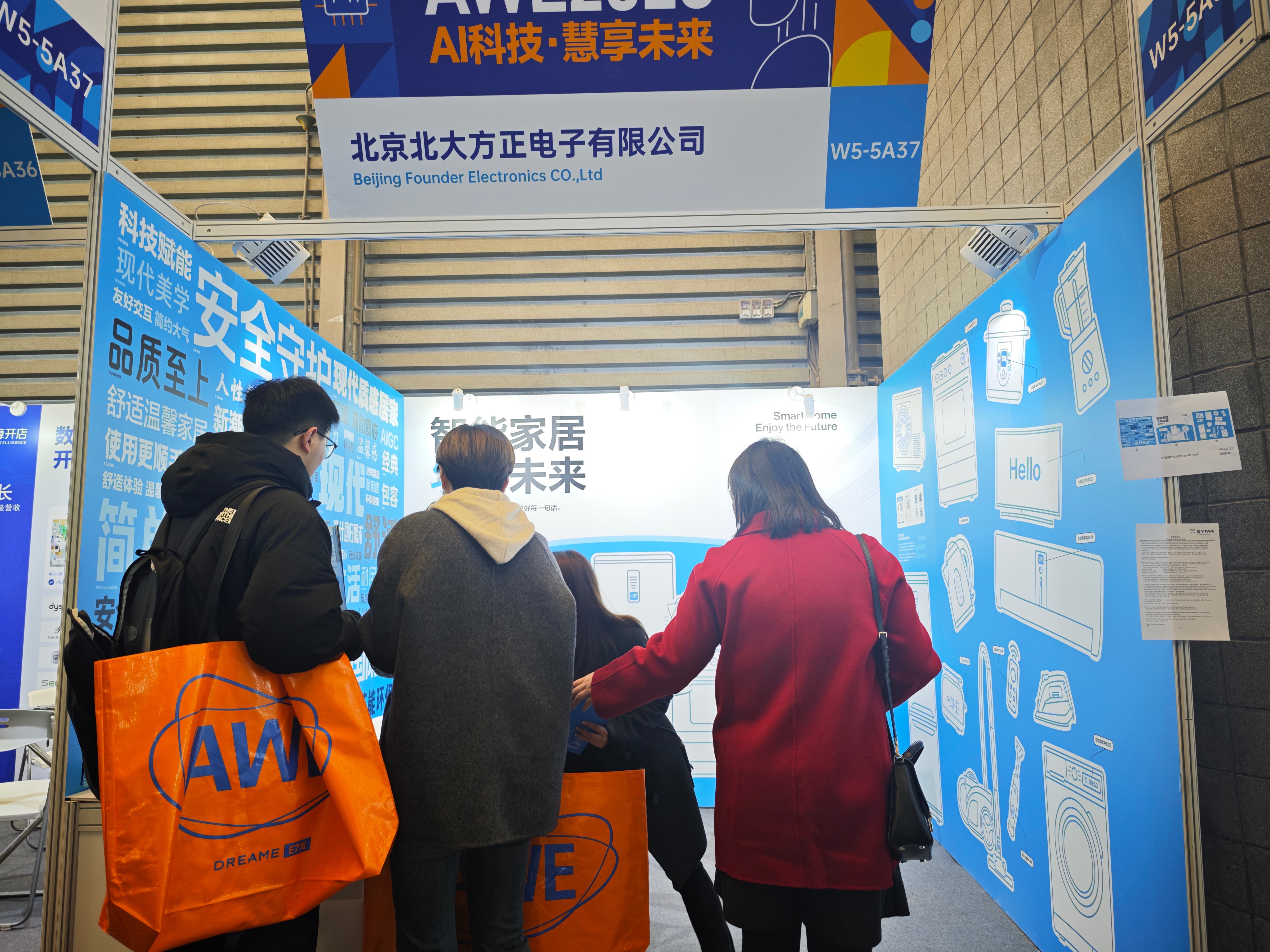
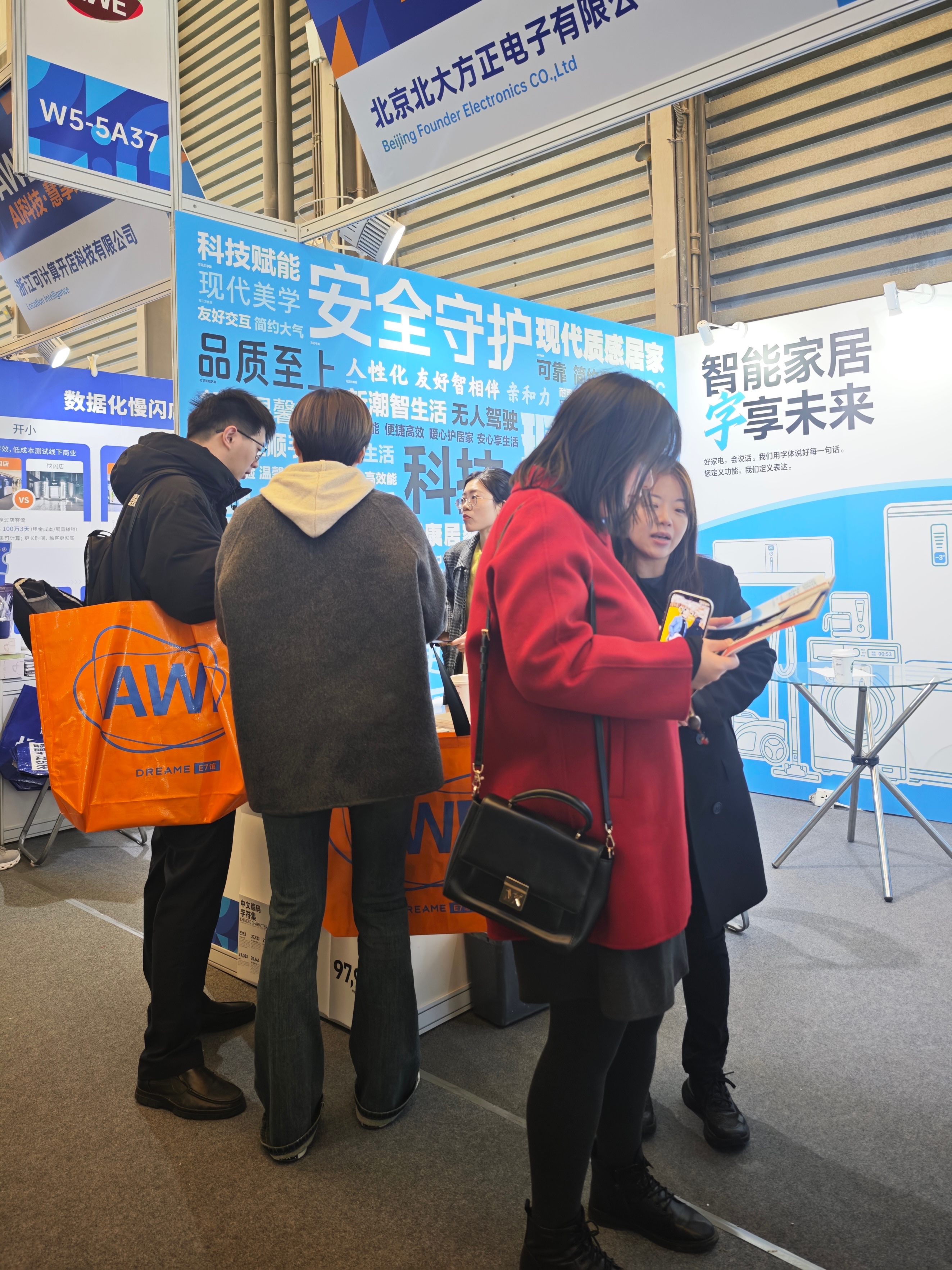
方正字库展位现场图
这意味着,从空调、冰箱到洗衣机,每一台贴有能效标识的家电产品,其背后的能效等级、耗电量等关键信息,都通过方正字体精准触达给消费者。方正字库相关人员表示,通过为标识管理提供字体支持,方正字库间接服务于中国数以亿计的家电产品,以文字之力助推行业节能环保升级。目前,大量家电品牌已积极采用规范标识,向绿色化、规范化方向快速发展。方正字库的标准字体方案覆盖工业设备面板、功能操作界面、大屏终端显示等多重场景,为家电行业提供可靠的基础字体支撑。
驱动品牌升级:以定制字体打造差异化竞争力
在满足行业共性规范的基础上,方正字库本次重点展示了其定制字体能力。对于追求品牌差异化的企业而言,标准字体满足基础传达,定制字体方能承载品牌独特基因。方正字库以专业的定制字体服务,助力企业将品牌理念注入每一处文字细节,实现视觉识别从可用到专属的战略升级。
案例一:PICO——以技术突破定义VR专用字体标准
以VR头部品牌PICO为例,2022年PICO品牌全面升级,确立“成为领先的世界级XR平台”的全新愿景。伴随品牌焕新,方正字库与PICO携手打造的首款VR专用定制字体PICO Sans,正是这一品牌升级战略的关键载体。
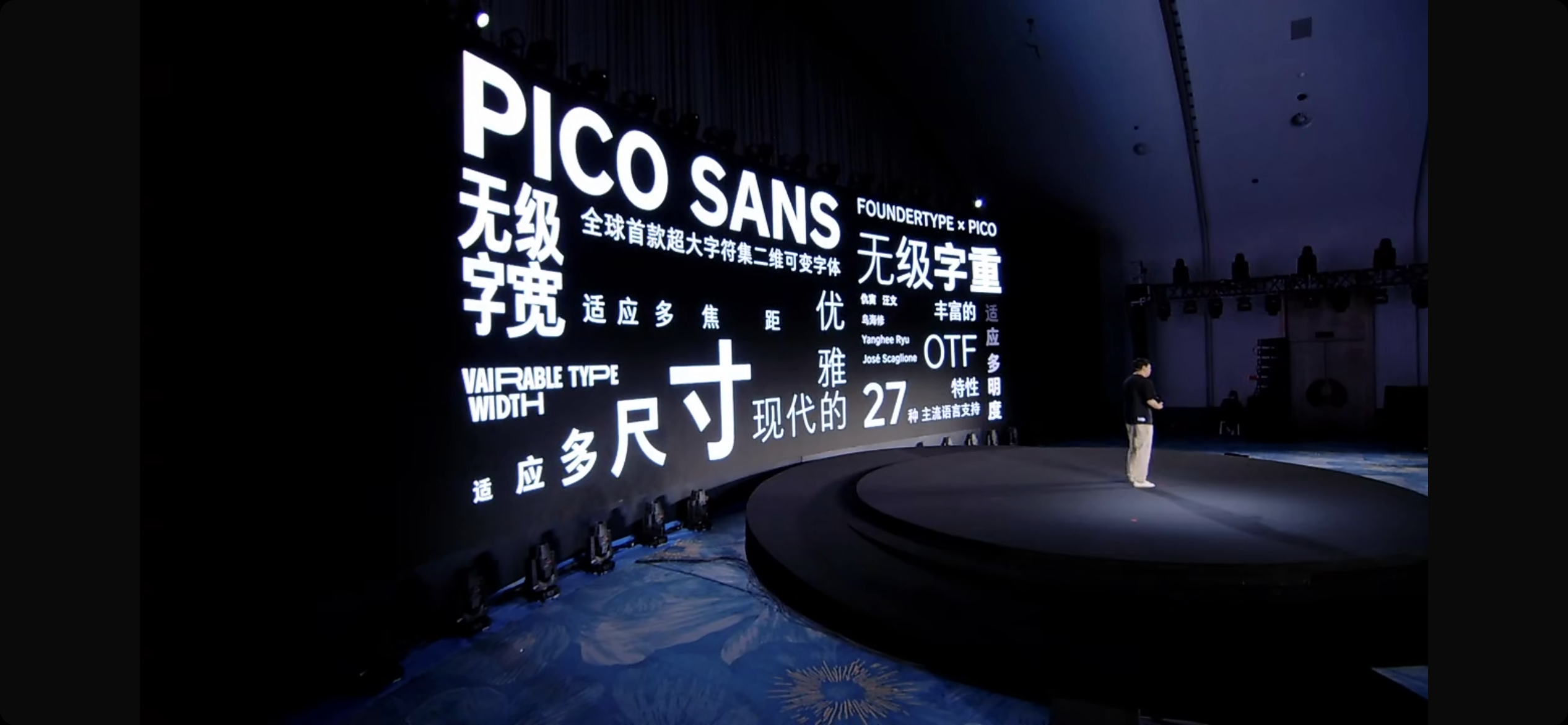
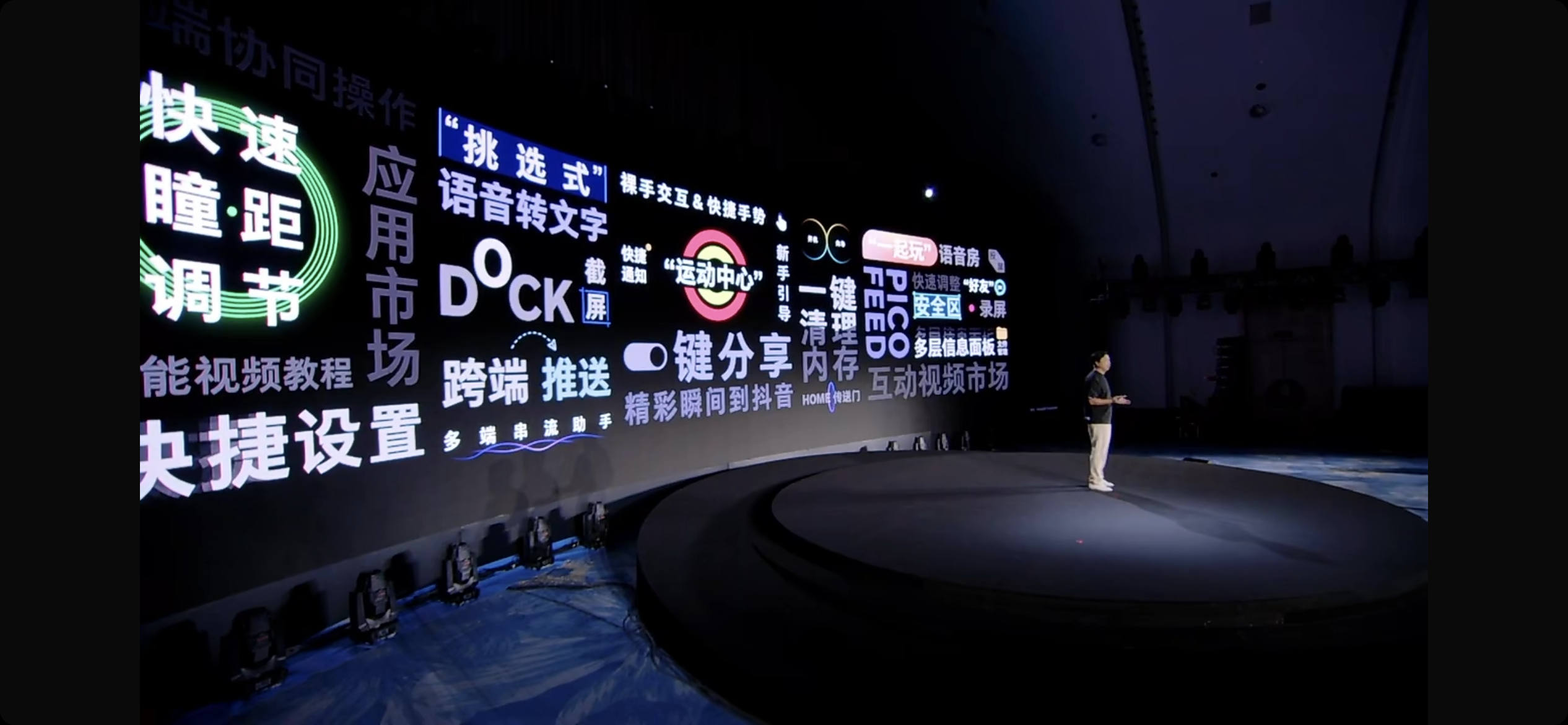
PICO Sans是首款实现字重、字宽二维可变的定制字体,同时支持简繁中文、日、韩、英、德、法等多个语种,以统一的视觉语言支撑PICO全球化战略,助力品牌在不同市场保持形象一致性。
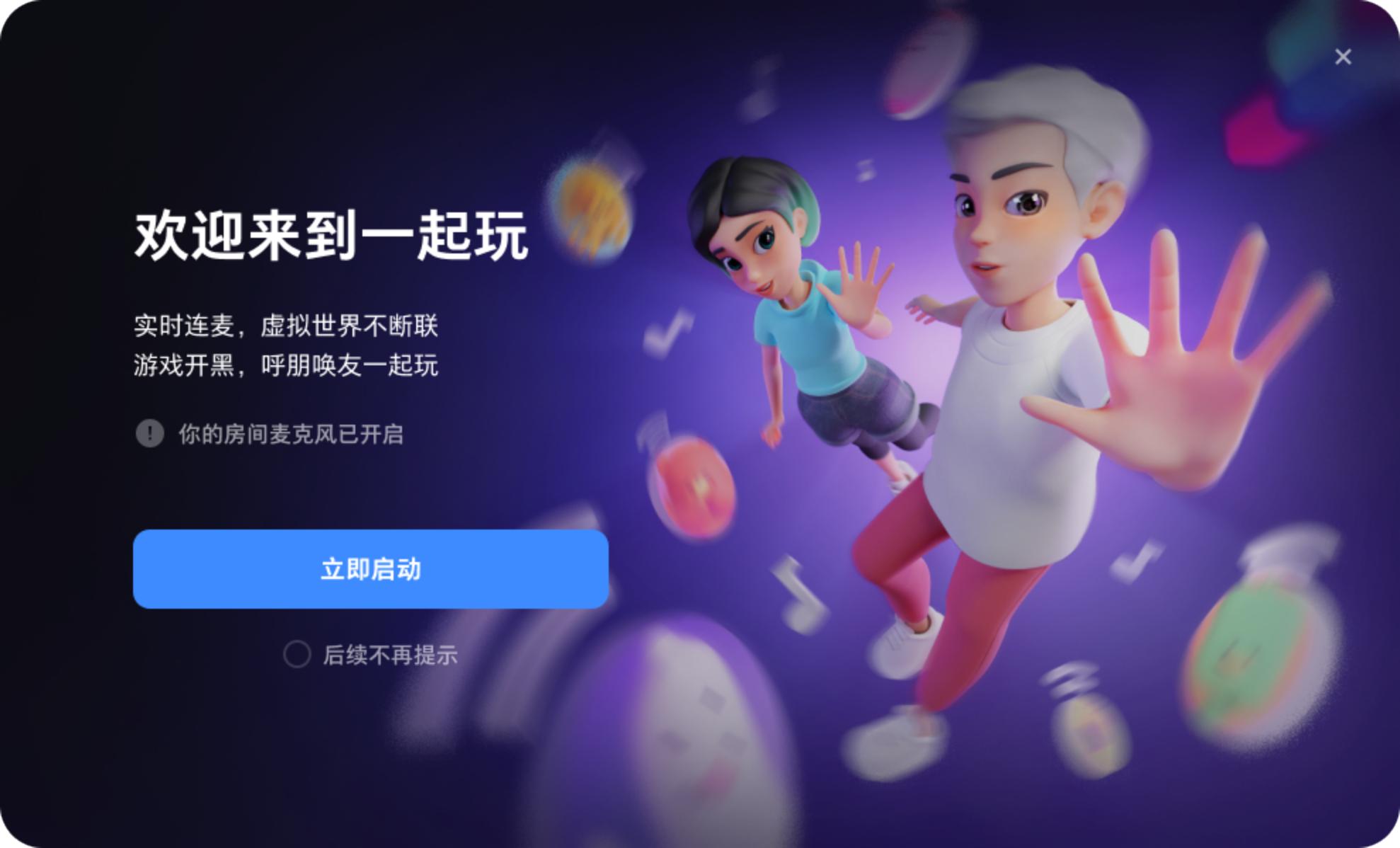
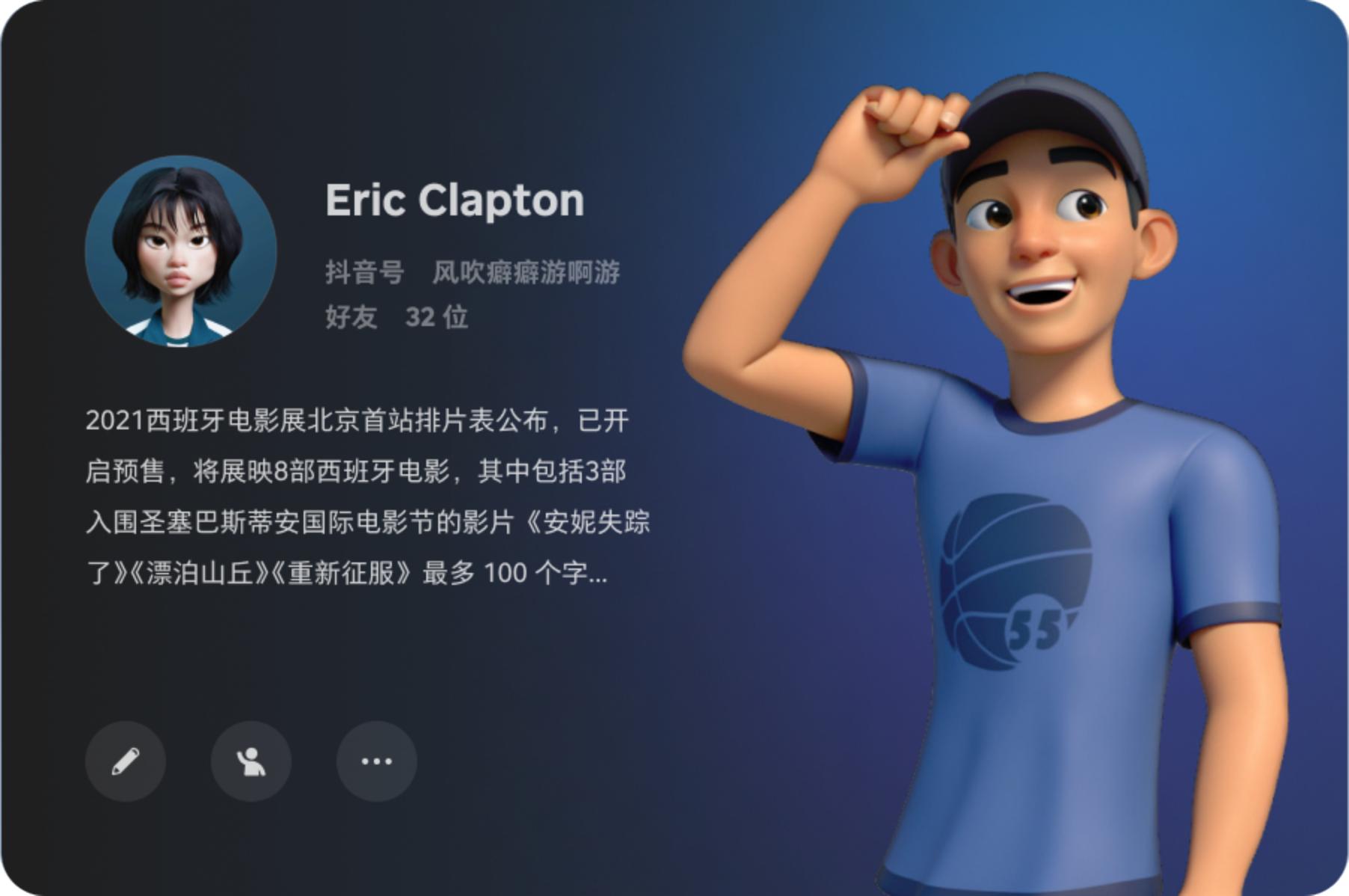
PICO Sans应用图展示
PICO Sans不仅是一款字体,更是PICO品牌升级战略的重要组成——它通过技术突破提升产品力,通过统一识别强化品牌力,通过多语种能力支撑全球化布局。
案例二:美的——以品牌字体沉淀企业战略价值
美的集团的定制案例则展现了字体作为品牌资产的战略纵深。在美的向AI智能化全面转型的进程中,方正字库为其量身打造的“美的无界联动体”,被赋予“可在美的任何载体上使用”的使命。
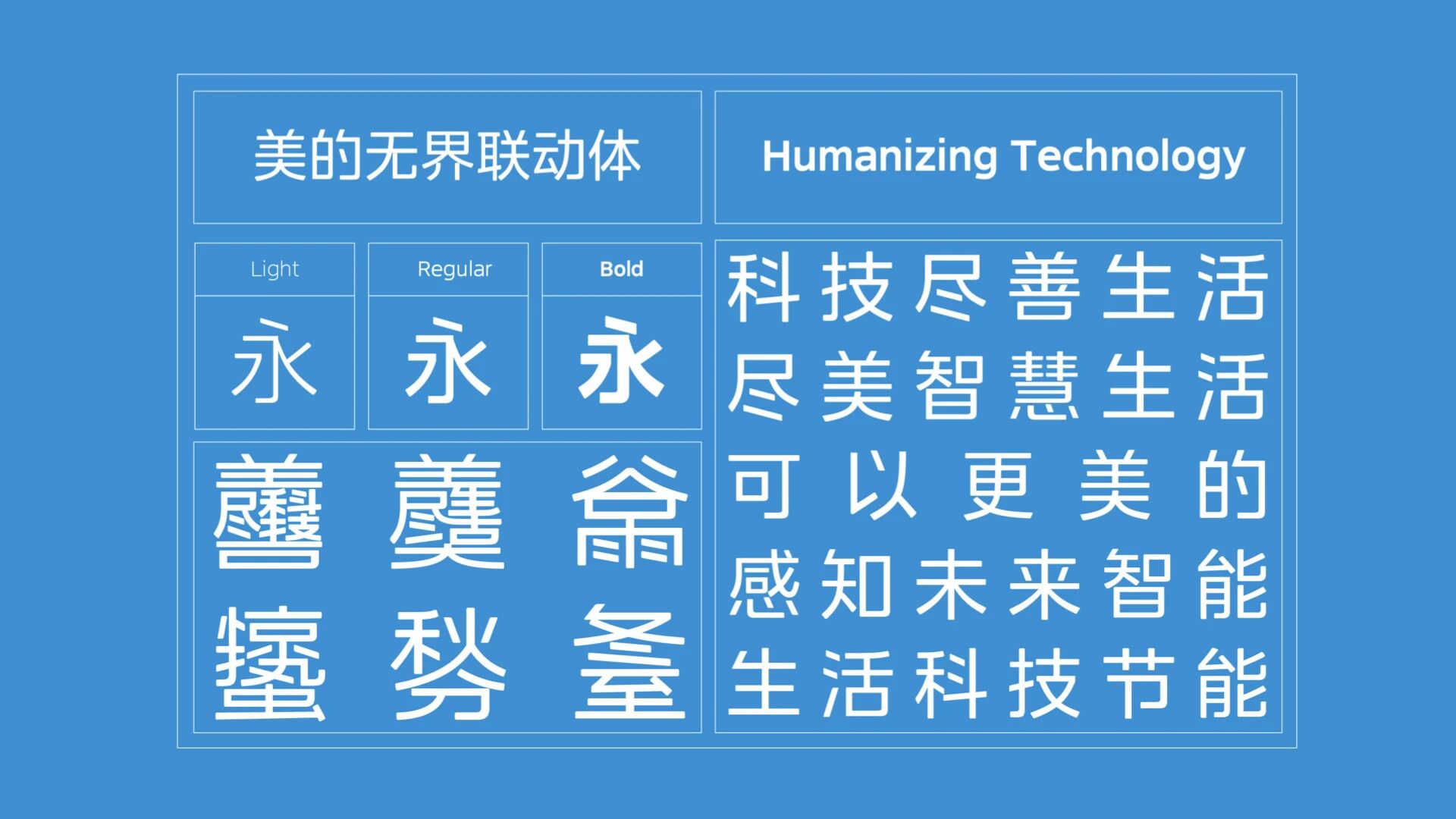
字体在设计之初便精准适配产品内嵌屏幕、功能面板、智能终端等全场景需求,通过连笔设计传递智能感与先锋感。字体从“人性科技”内核出发,以圆润线条传递品牌温度,以挺拔字形彰显年轻活力,以开放中宫传递包容态度,统一了品牌全链路视觉形象。美的无界联动体以独特的视觉语言诠释“科技尽善,生活尽美”的品牌理念,让每一次文字交互都成为品牌价值的传递。
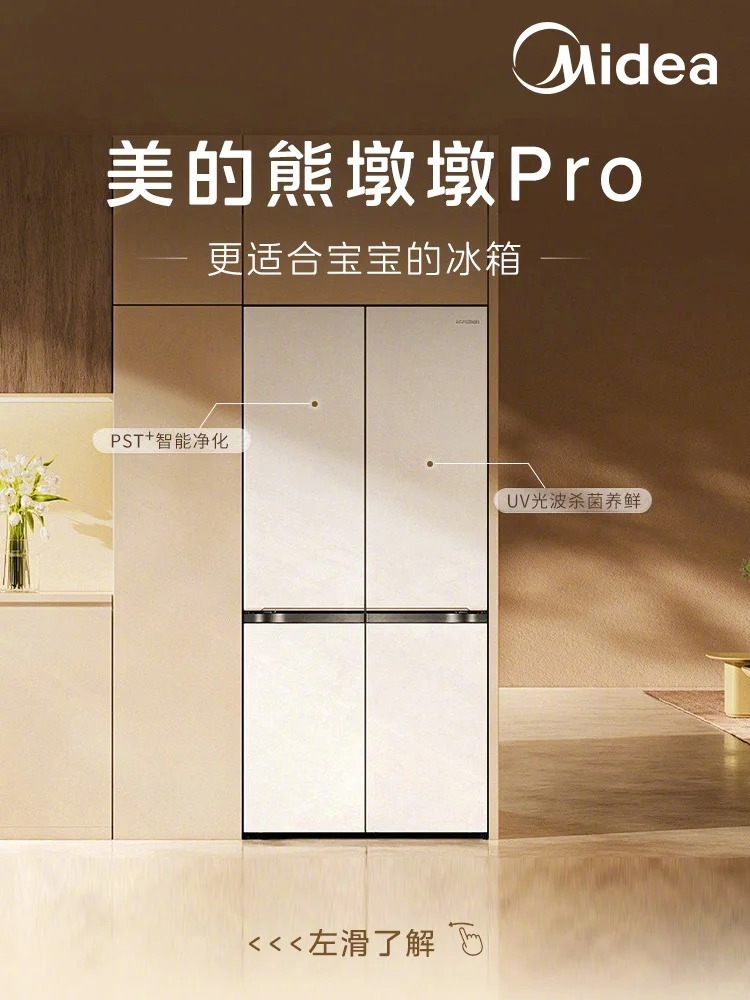
美的无界联动体应用图展示
这不仅是艺术设计与工业设计的和谐共创,更是品牌理念与字体形象的深度融合——在智能化进程中,字体作为品牌资产,正在成为连接品牌与用户的无声纽带。
拓展应用边界:以多元方案服务品牌全链场景
除了满足行业基础的标准字体和承载品牌个性的定制字体,本次展会还全面呈现了方正字库在更多业务场景下的专业能力。面对企业日常运营中纷繁复杂的用字需求,方正字库的产品与服务同样提供全面支撑,覆盖家电企业的多元应用场景:
品牌宣传场景:不管是线下招商会、新品发布会的物料制作,还是线上电商详情页、社交媒体传播,不同场景对字体的要求各不相同。线下物料需要字体适配喷绘、印刷等制作工艺,确保视觉效果的完美呈现;线上宣传则需要字体准确传递品牌氛围,在第一时间吸引用户关注。方正字库丰富的字体产品,能够满足品牌在各种沟通场景下的用字需求。
出海业务:在经济全球化的趋势下,家电企业积极拓展海外市场,新兴市场的小语种消费者成为重要开拓目标。方正字库能够帮助企业选择符合多元语言环境的多语种字体方案,确保品牌在不同国家和地区都能以统一的视觉形象与当地消费者有效沟通,支撑企业的全球化战略。
内嵌字体:从智能冰箱的触控面板到空调的显示屏,从投影仪的操作界面到VR眼镜的沉浸视效,家电产品的交互体验高度依赖屏幕显示。方正字库深耕嵌入式字体领域,为各类智能终端提供稳定、清晰的内嵌字体支持,确保文字在不同分辨率、不同亮度的屏幕上始终如一地精准呈现,以专业技术赢得行业信赖。
字体资产管理:对于采购字体品类多、内部使用人员广的家电品牌而言,字体的统一管理和合规监测一直是品牌资产管理的痛点。方正字库的企业字体资产服务平台,让设计人员可以更方便快捷地使用字体,同时帮助管理人员全面了解字体使用情况,实现品牌字体资产的高效、合规管理。
展会期间,方正字库展台吸引了众多行业专家与品牌代表驻足交流,共同探讨AI时代下字体应用的无限可能。从满足行业基础规范的“通用语言”,到承载品牌独特基因的“专属表达”,再到覆盖全链场景的“系统化管理”——方正字库愿以专业设计力量,助力企业以文字之力塑造差异化视觉体验,赋能行业数字化新视界。欢迎通过官方渠道与我们联系。